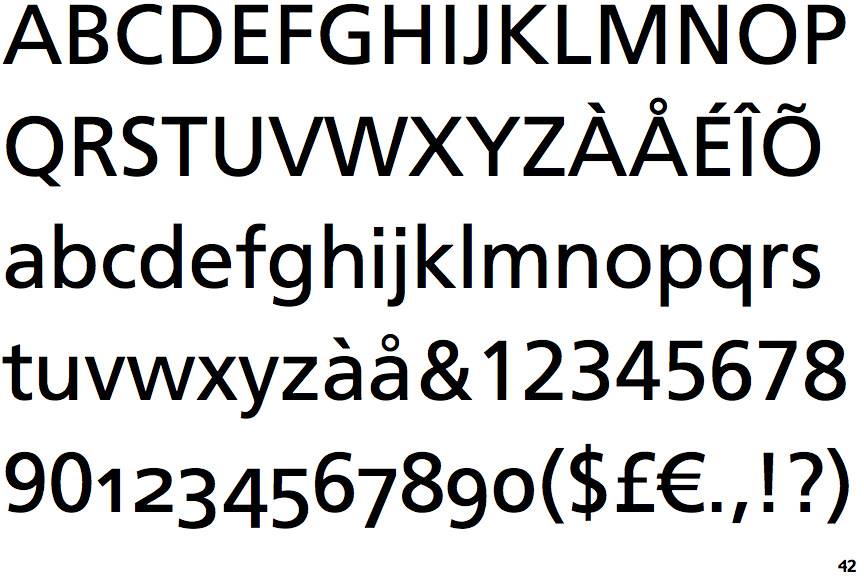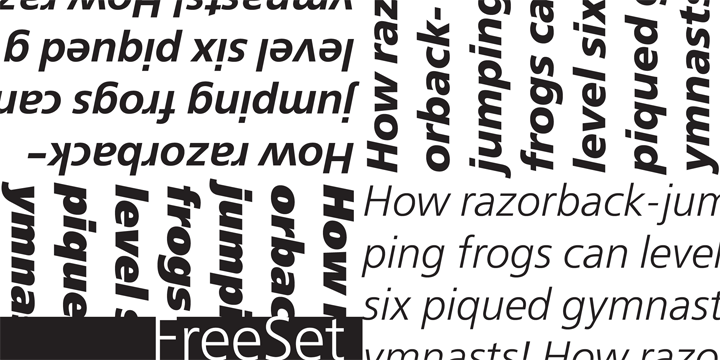
Шрифт freeset
Название: Шрифт freeset
Открытый гротеск, который работает как в текстовом, так и акцидентном наборах. Например, он подойдёт и для технической документации, и для плакатов.